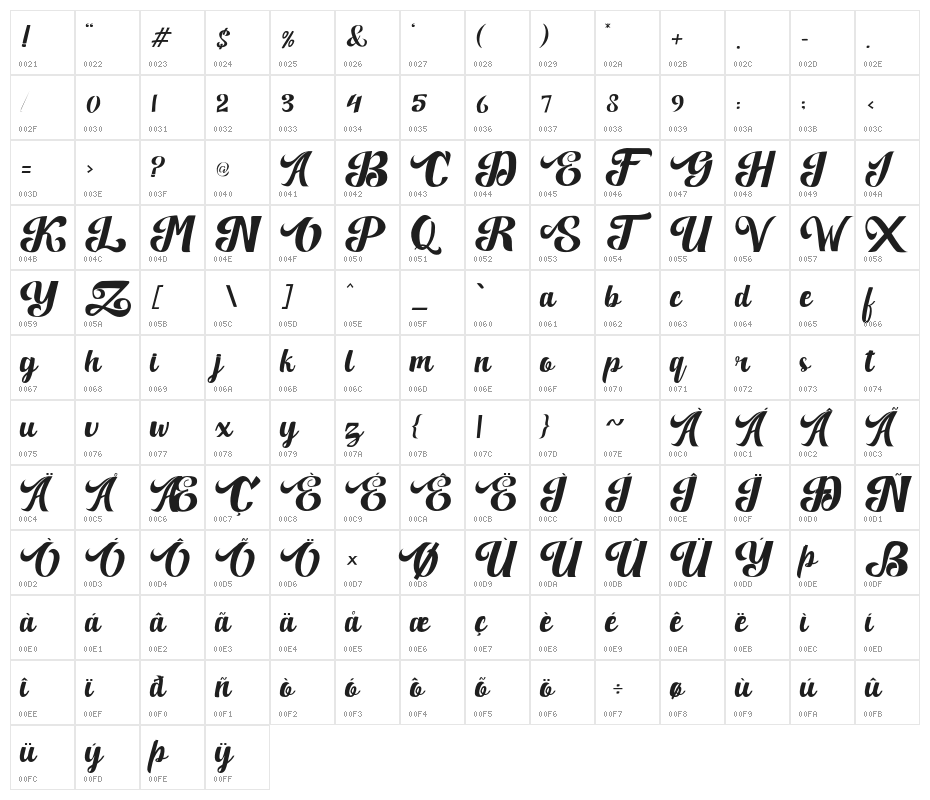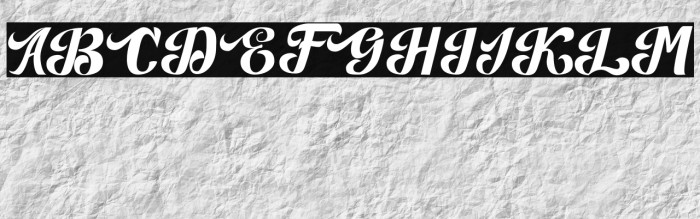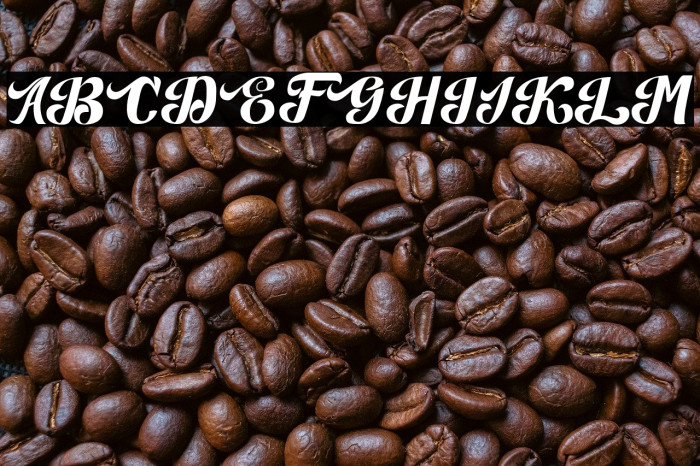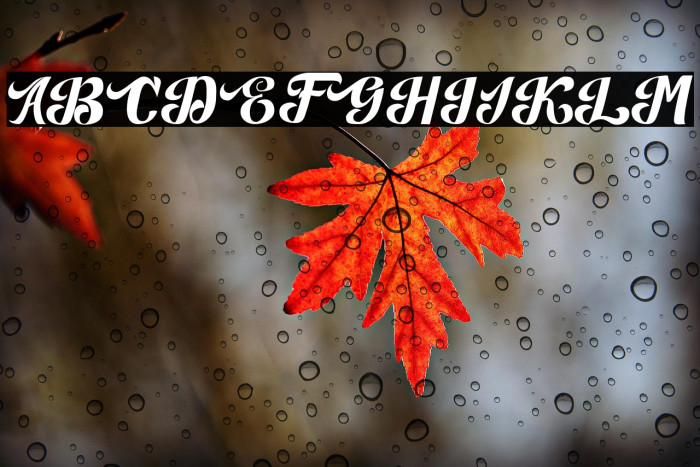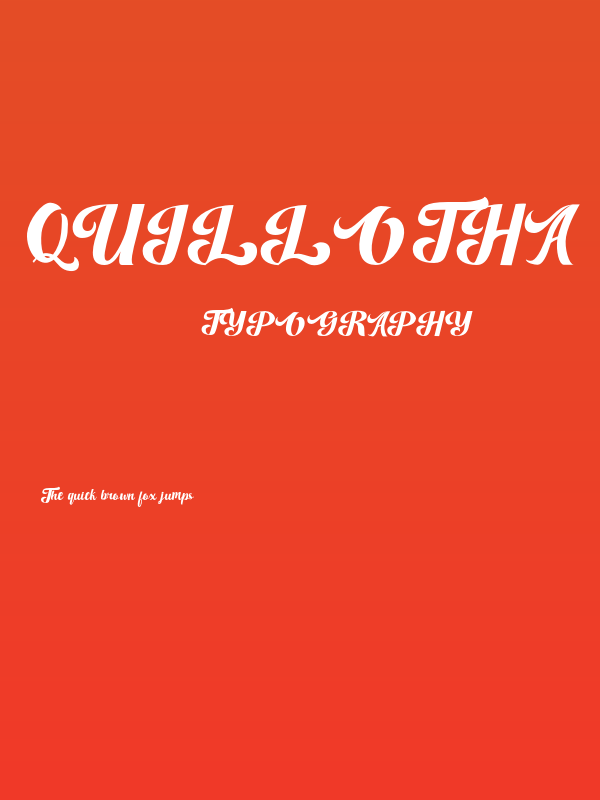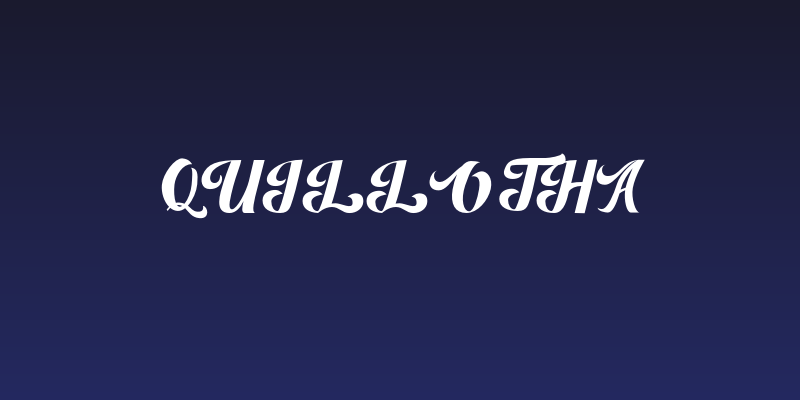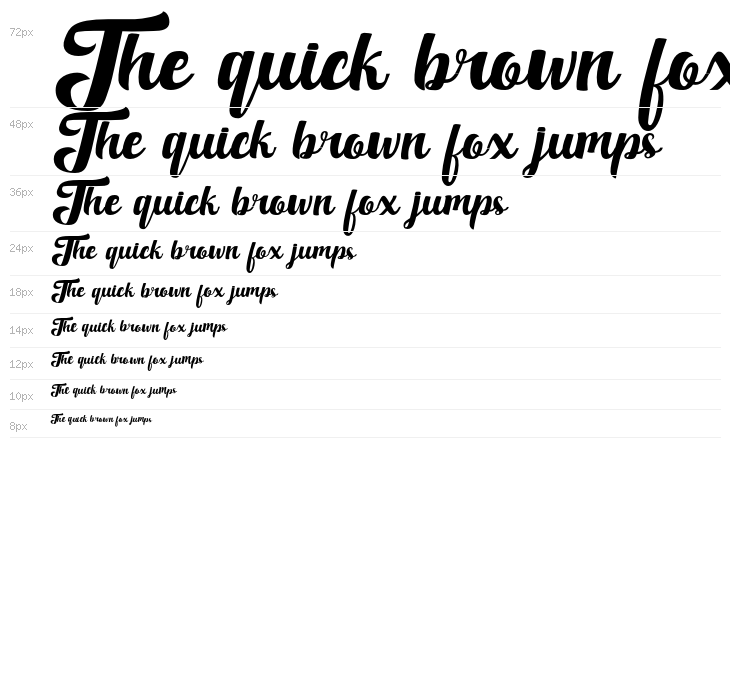
Quillotha Font
✎ Script
| Kategorien | Script |
| Anwendungsfall | Logos, Headlines, Invitations |
| Vorgeschlagene Projekte | Ideal for wedding invitations, branding projects, logo design, and decorative headings. |